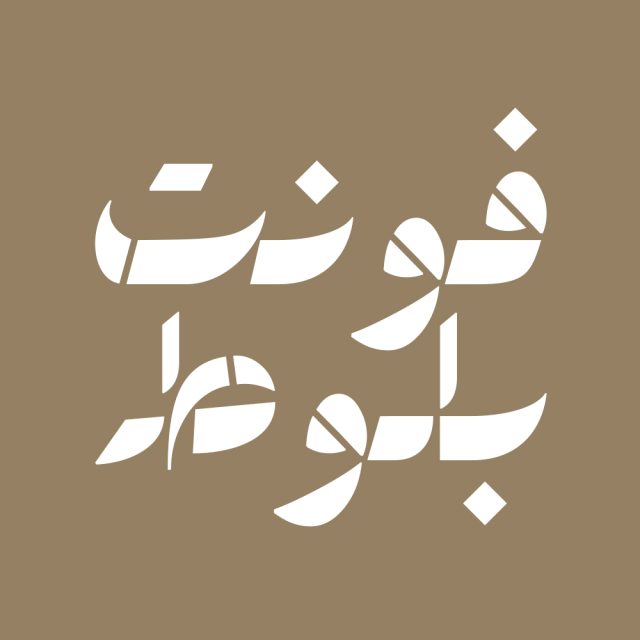
فونت فارسی بلوط Baloot Font
فونت فارسی بلوط فونتی است نمایشی، که بهترین کارایی‌ آن در عبارت‌های کوتاه است. شخصیت فونت بلوط با برش‌های استنسیلی سعی دارد از حالت رسمی و سنتی که در بن‌مایه‌اش وجود دارد بگریزد و خود را در قالب‌های مدرن جا کند.
فضاهای خالی در زوایای مختلف به بلوط حرکت و پویایی می‌دهد، چشم را درگیر می‌کند، و با بازیگوشی قابلیت و ظرفیت آن را گسترش می‌دهد.
فونت بلوط نسخه فارسی و ویرایش شده فونت عربی تقاصیم میباشد که فارسی سازی و بهینه شده و همچنین حروف لاتین به آن اضافه شده است. در ادامه برای شما نمونه تایپ های این محصول حرفه ای رو آماده کردیم که میتونید مشاهده کنید.
• مناسب طراحی بسته بندی ها و چاپ
• فونت ویژه تبلیغات محیطی
• فونت طراحی کاور اینستاگرام
• فونت حرفه ای برای تولید محتوا
• فونت فارسی طراحی وبسایت
• فونت طراحی لوگو تایپ فارسی
• مناسب استفاده در تابلو های چلنیوم و طراحی حروف